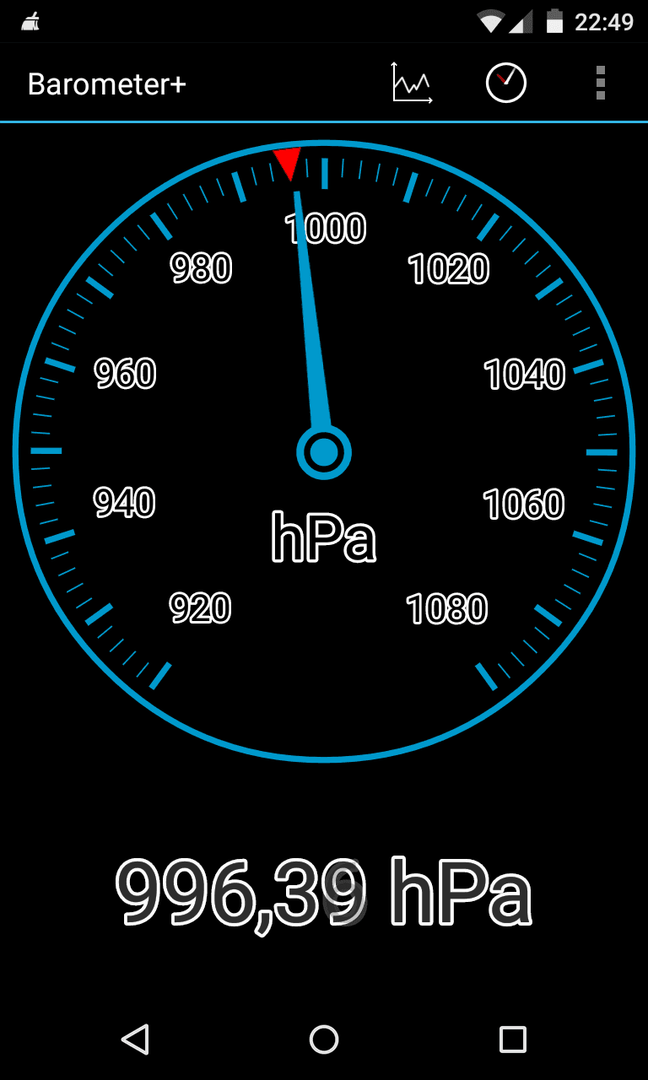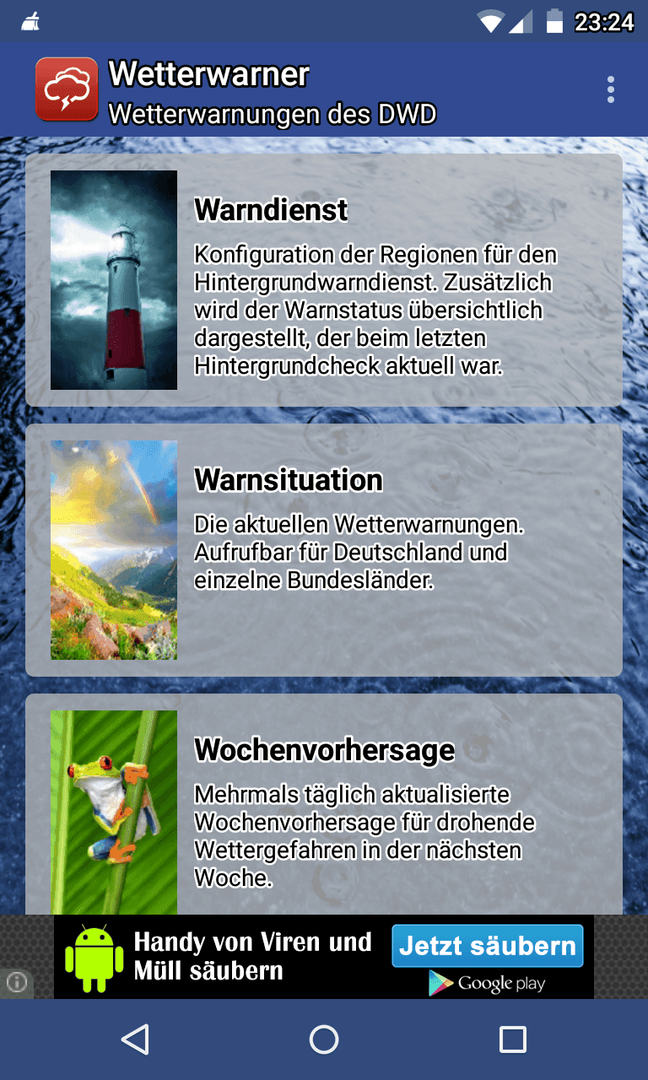
seit einiger Zeit wundere ich mich über die schlechte Lesbarkeit der Anzeige meines N4 (Android 5.1, LMY47O). Hier wird teilweise eine andere Schriftform eingefügt!
Ich habe mal exemplarisch 2 Screenshots beigefügt. Hat jemand für diesen Effekt eine Erklärung oder ist das neuerdings durch Android 5.1 bedingt.
Wie kann man das wieder zurückstellen?